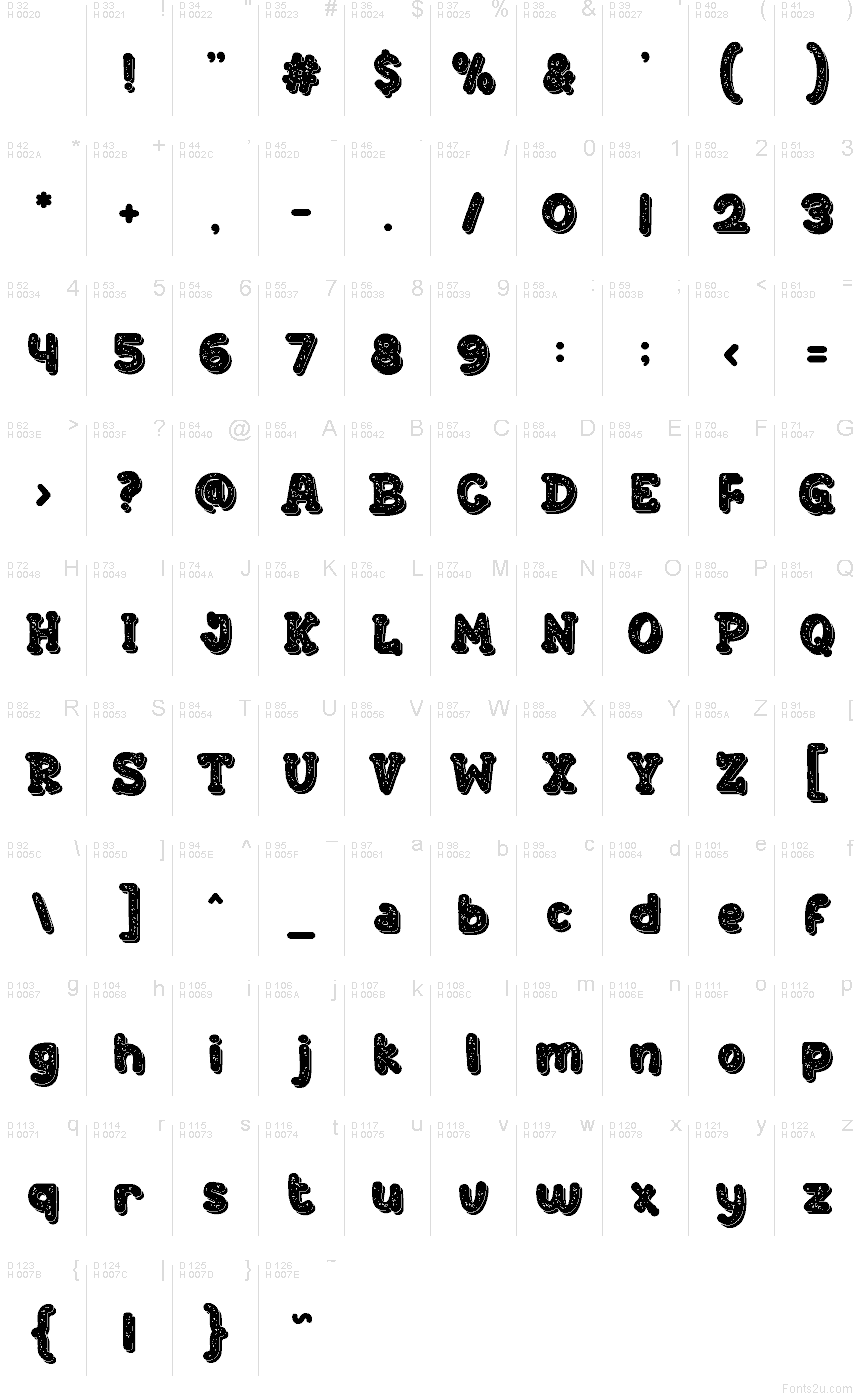
Crayon Craft Five
Crayon Craft Five od Putracetol Studio je bezplatné dekoratívne písmo, ktoré pripomína kresbu pastelkou. Vyznačuje sa hrubými, zaoblenými tvarmi a jemnými škrabancami, ktoré vyzerajú, akoby boli do písmen vyryté. Táto kriedová, opotrebovaná textúra dodáva písmu školský, ručne kreslený charakter, zatiaľ čo bucľatá silueta ho približuje skôr k nápisom v kreslených seriáloch ako k drsnému grunge štýlu.
Skvele vynikne na obálkach detských kníh, kreatívnych obaloch, školských plagátoch, narodeninových pozvánkach alebo hravých náhľadoch na YouTube, kde ošúchaný povrch písma dotvára príbeh. Najlepšie poslúži v krátkych nadpisoch a na štítkoch, pretože široké tvary a škvrnitá textúra dodajú každej vete vzhľad obrázka nakresleného hrubou voskovkou.